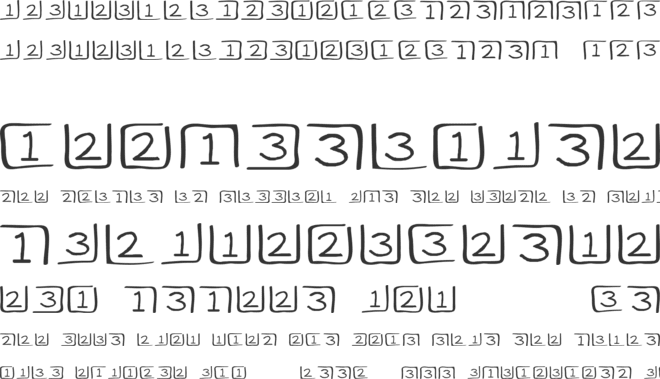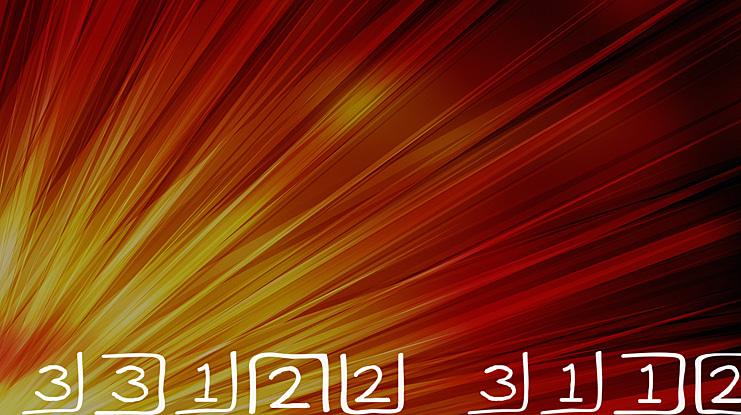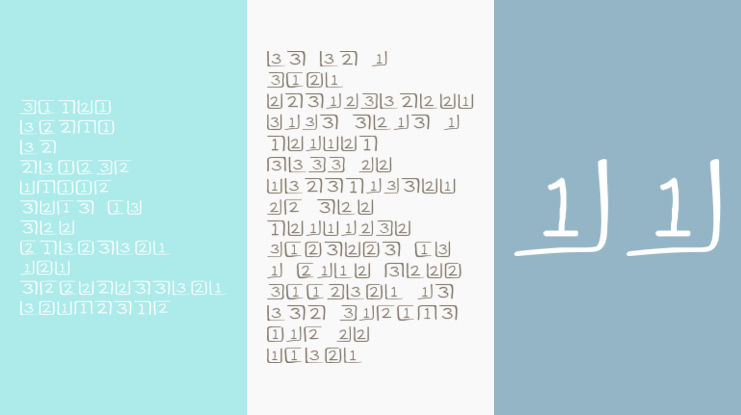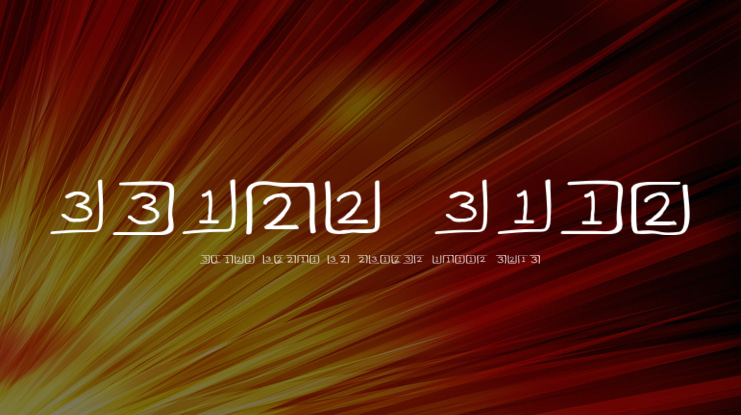
Clave Cajn Font
Clave Scout Cajón, Basada en el pictograma de una cuadricula de 3x3 en cada cuadricula se ubican 3 letras incluyendo la Ñ, en la casilla superior-izquierda se ubica la A, B y C siguiendo al cajón de la derecha con la D, E F.
En algunos grupo de colombia en lugar de números los cajones se hacen mas grandes y se ubica un punto; si este esta en el extremo izquierdo es la primera letra, si esta en el centro es la segunda y si esta al extremo derecho es la tercer y ultima letra del cajón.